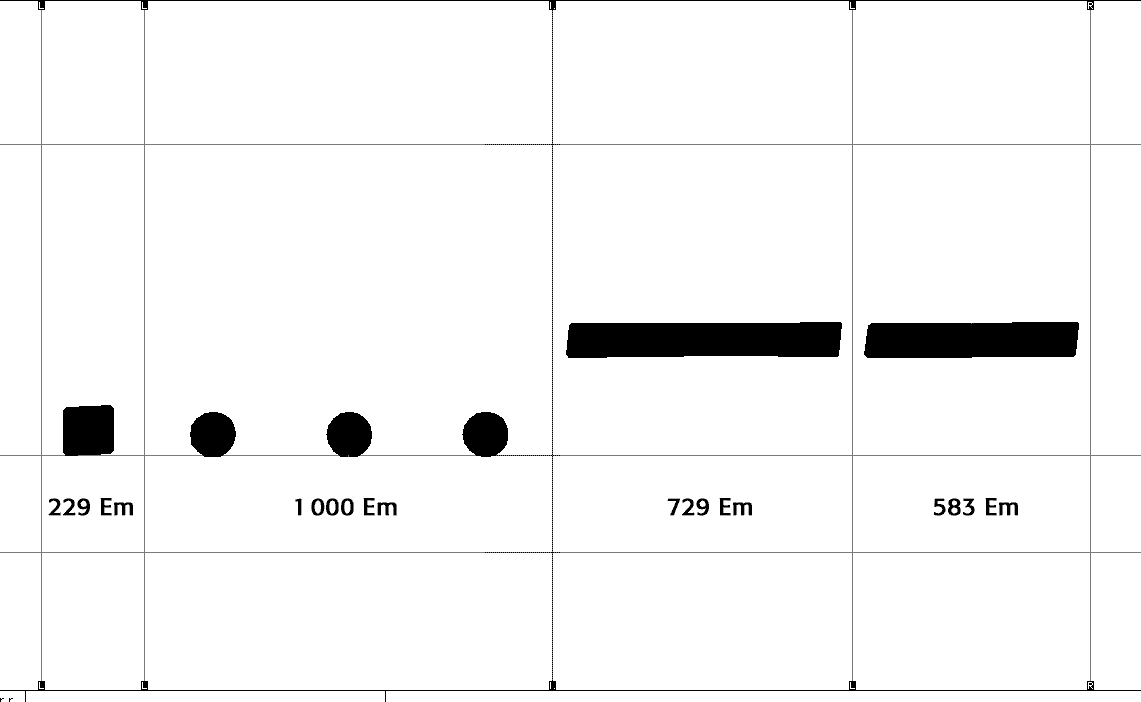
À la demande d'un colistier, Jacques André, je reposte mon petit dessin d'hier, en indiquant la chasse de chacun des caractères du Formata en cause dans la discussion de l'autre jour, ce qui permet d'en visualiser les talus d'approche (espaces à gauche et à droite de la partie imprimable). En dessous des caractères, j'ai indiqué la valeur de la chasse, sachant que par construction « 1 000 Em » est l'unité de base de la police considérée et représente la valeur d'un cadatin. On voit bien que si les points de suspension (dont le dessin est par ailleurs fautif) ont une chasse d'un cadratin, le tiret demi-cadratiné chasse plus qu'un demi-cadratin (sic) et que le tiret cradratiné chasse moins qu'un cadratin (resic) NB. Fichier joint, monté d'après des copies d'écran dans Fontographer. Bonne fin d'après-midi à tous.